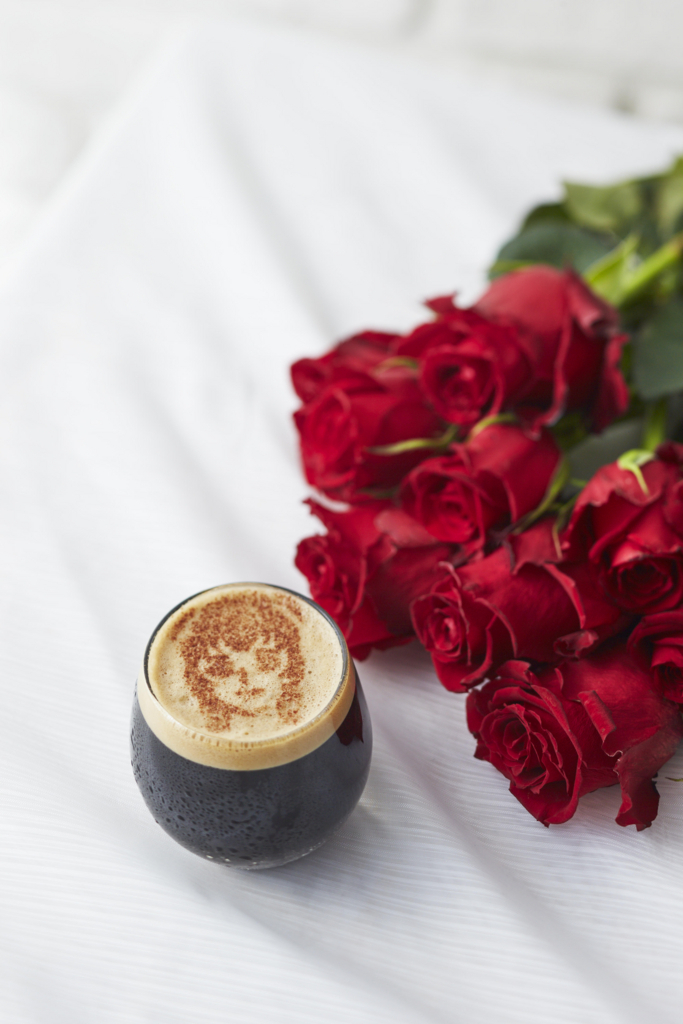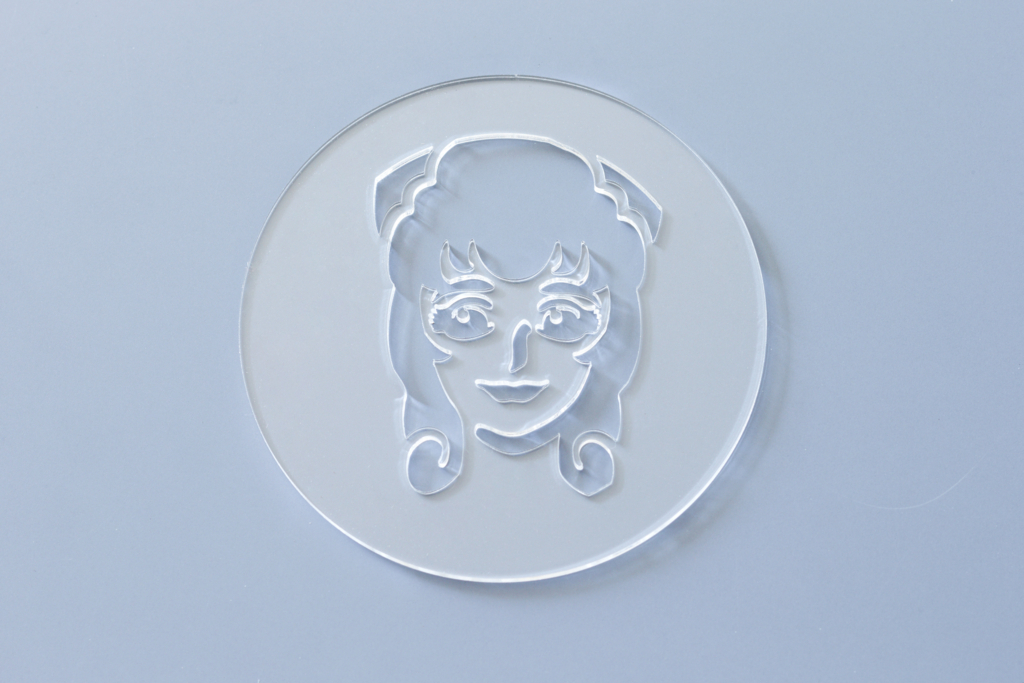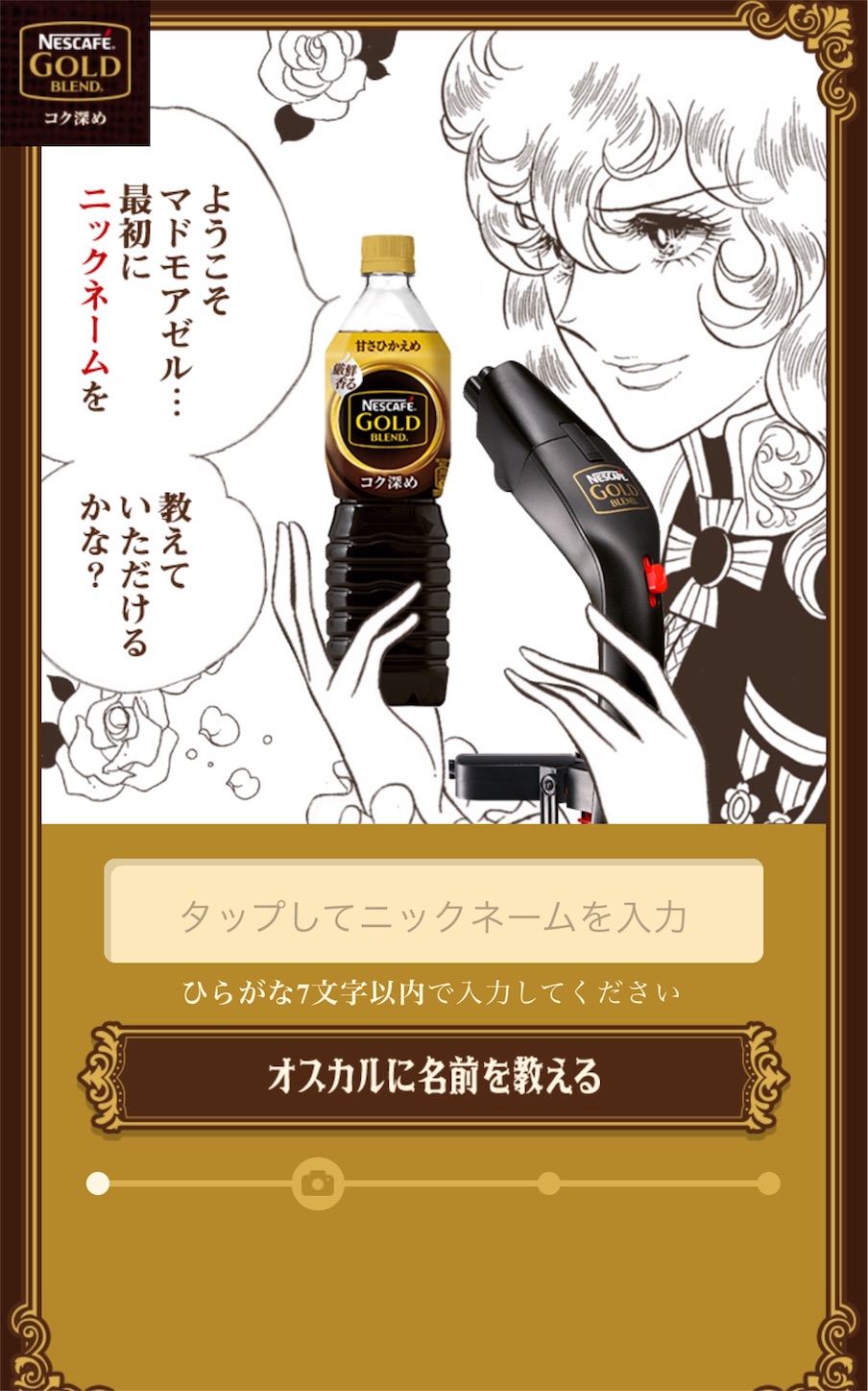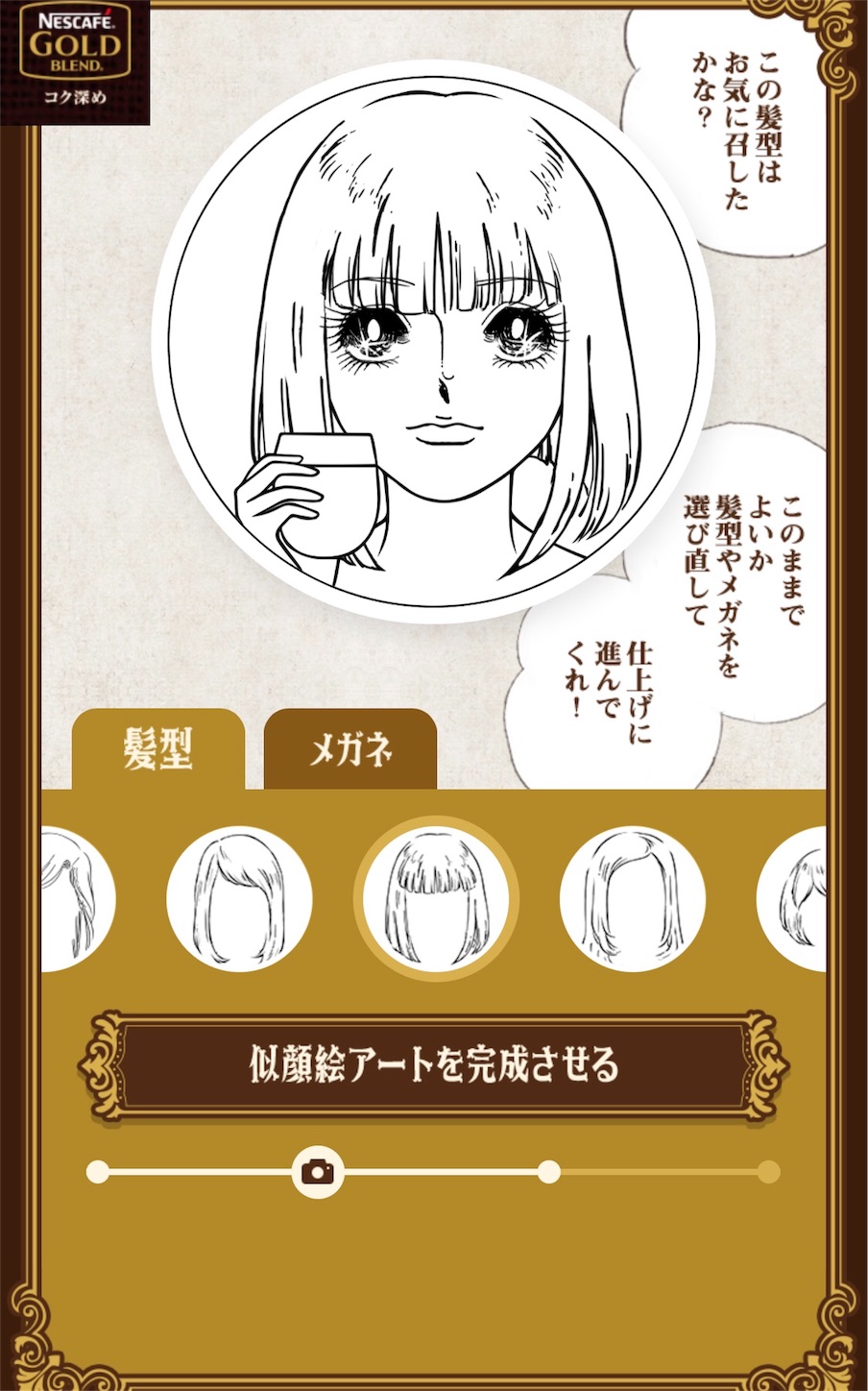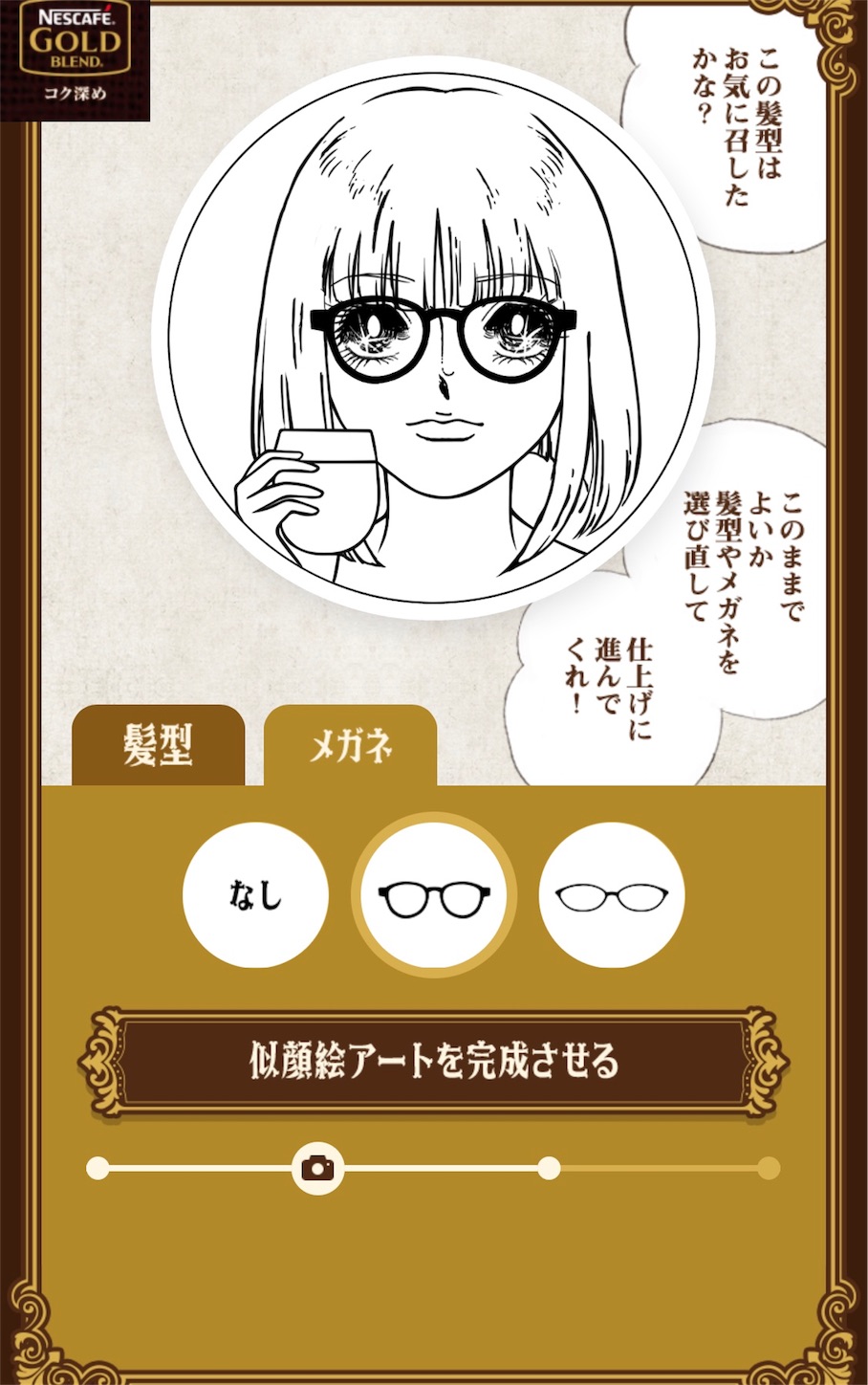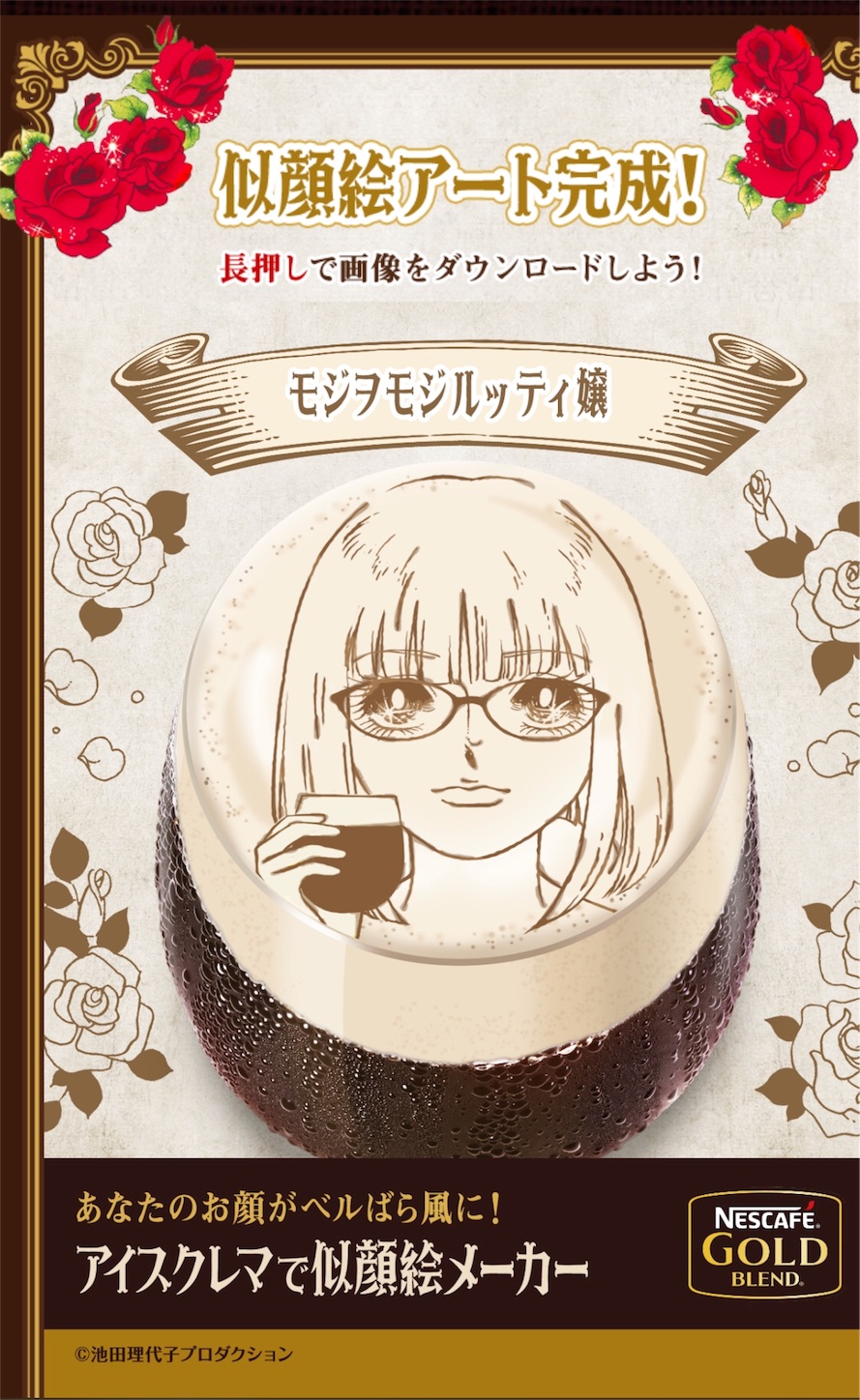
「アイスクレマで似顔絵メーカー」でベルばら風の似顔絵が作成できる!
ネスレは、「ネスカフェ アイスクレマ プロジェクト」の一環として、人気漫画「ベルサイユのばら」とコラボレーションして、WEB上にアップロードした自分の顔写真を、最先端の顔認識技術を使用したプログラムにより、自動でベルばら風の似顔絵に生成する日本初のサービス「アイスクレマで似顔絵メーカー」を、2018年6月13日(水)から特設WEBサイト上で開始した。
「アイスクレマで似顔絵メーカー」~あなたのお顔がベルばら風の似顔絵に!~
「アイスクレマで似顔絵メーカー」は、自分の顔写真をWEB上にアップロードすると、プログラムが眉や目、鼻や口、輪郭などの顔の特徴を認識して、自動でベルばら風の似顔絵を生成する日本初のサービス。コンテンツで生成される似顔絵のパーツはすべて、ベルサイユの薔薇の作者である池田理代子先生が「ベルサイユのばら」をはじめとした作品で描かれたもの、また監修を手がけられたもの。
アイスクレマコーヒーの特長であるクレマ(泡)を活かし、他のアイスコーヒーではできないアイスクレマアートをデジタル上で展開される。
またこのサービスは、アプリをダウンロードしないで、スマホのブラウザ上で簡単に体験できる。
特設WEBサイトでは「ベルばら」の有名キャラクターがコーヒーの香りを閉じ込めるクレマ(泡)やまろやかな口当たりなど、アイスクレマコーヒーの特長について説明します。また「ネスカフェ ゴールドブレンド ハンディ アイスクレマサーバー」を、デジタル上で疑似体験しながら使用することもできる。
ベルばら風似顔絵をSNSや実際のラテアートでも楽しむことができるキャンペーンを実施
アイスクレマコーヒーや「アイスクレマで似顔絵メーカー」をSNS上や実生活でより多くのお客様に楽しめるように、SNSなどで使用できる、ベルばら風似顔絵のメッセージつきデコ画像や、アイスクレマコーヒーで実際にご自身のベルばら風似顔絵のラテアートを作ることができるオリジナルのステンシルシートを、抽選でプレゼントするキャンペーンを実施。